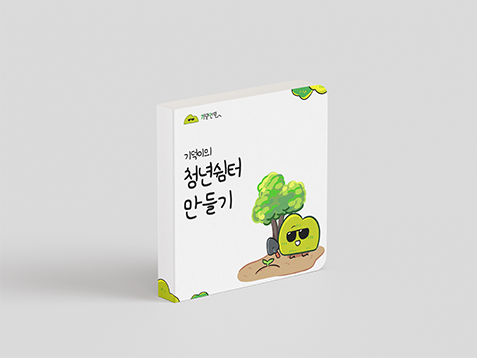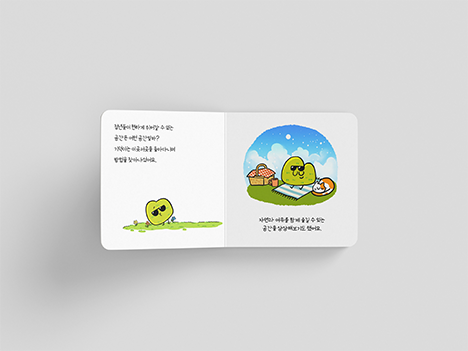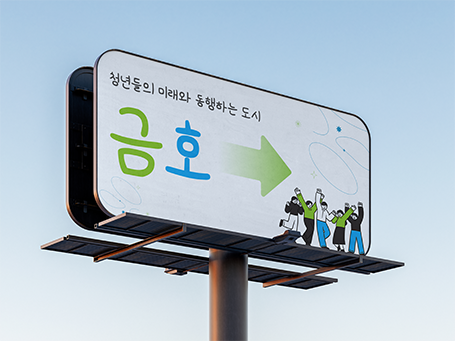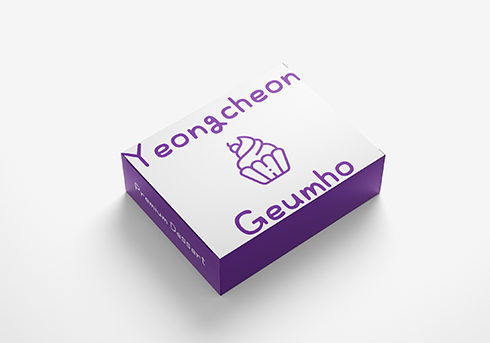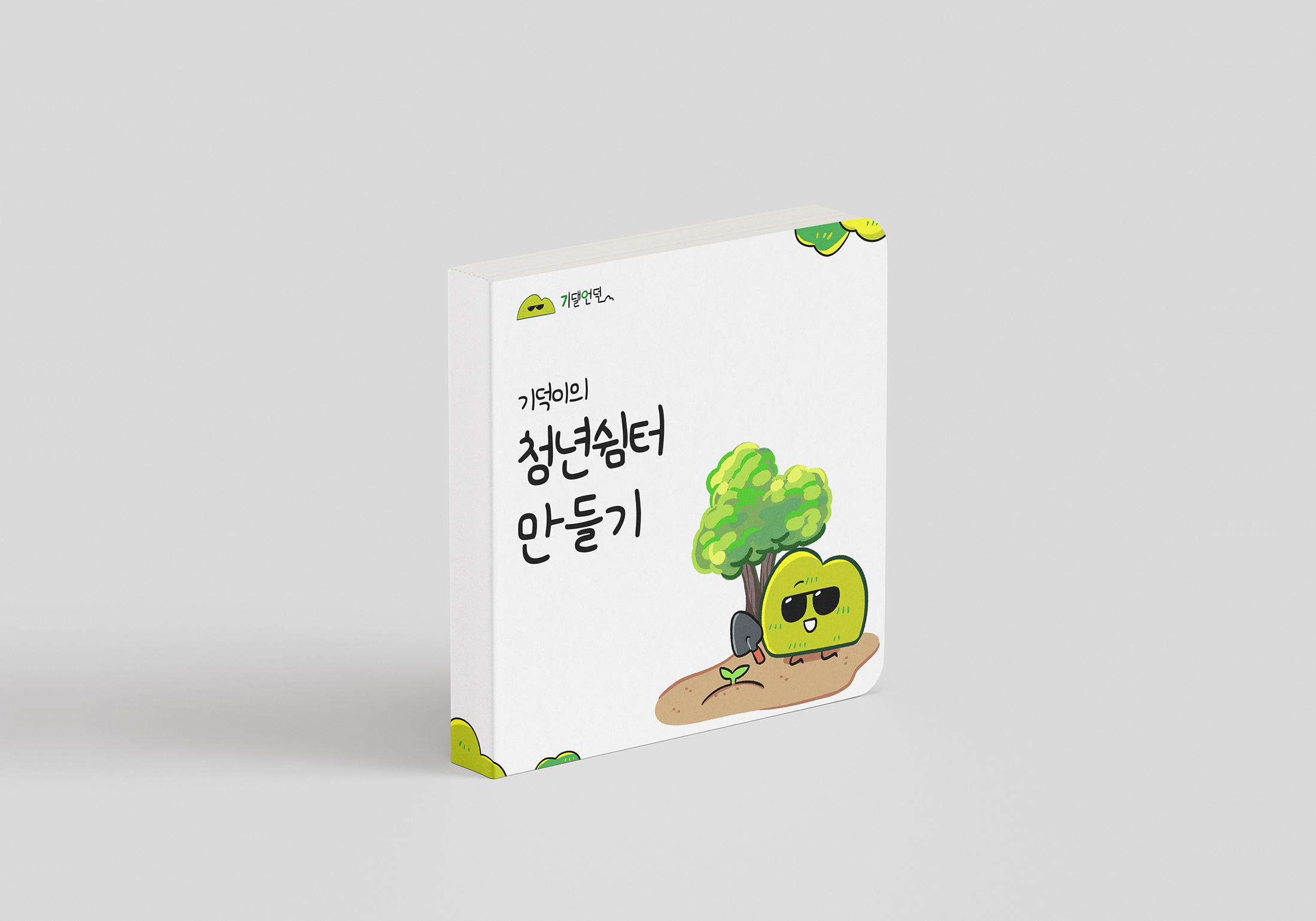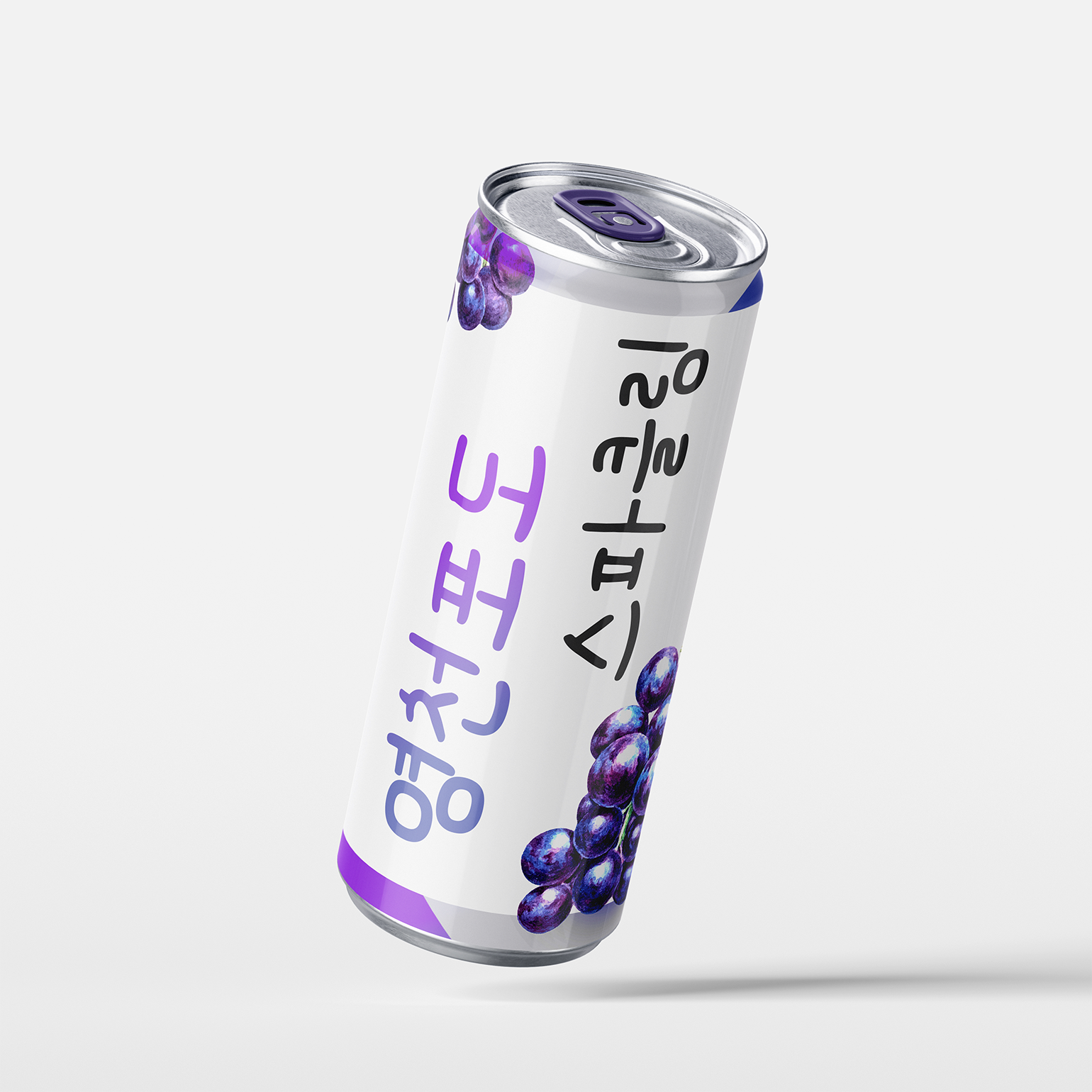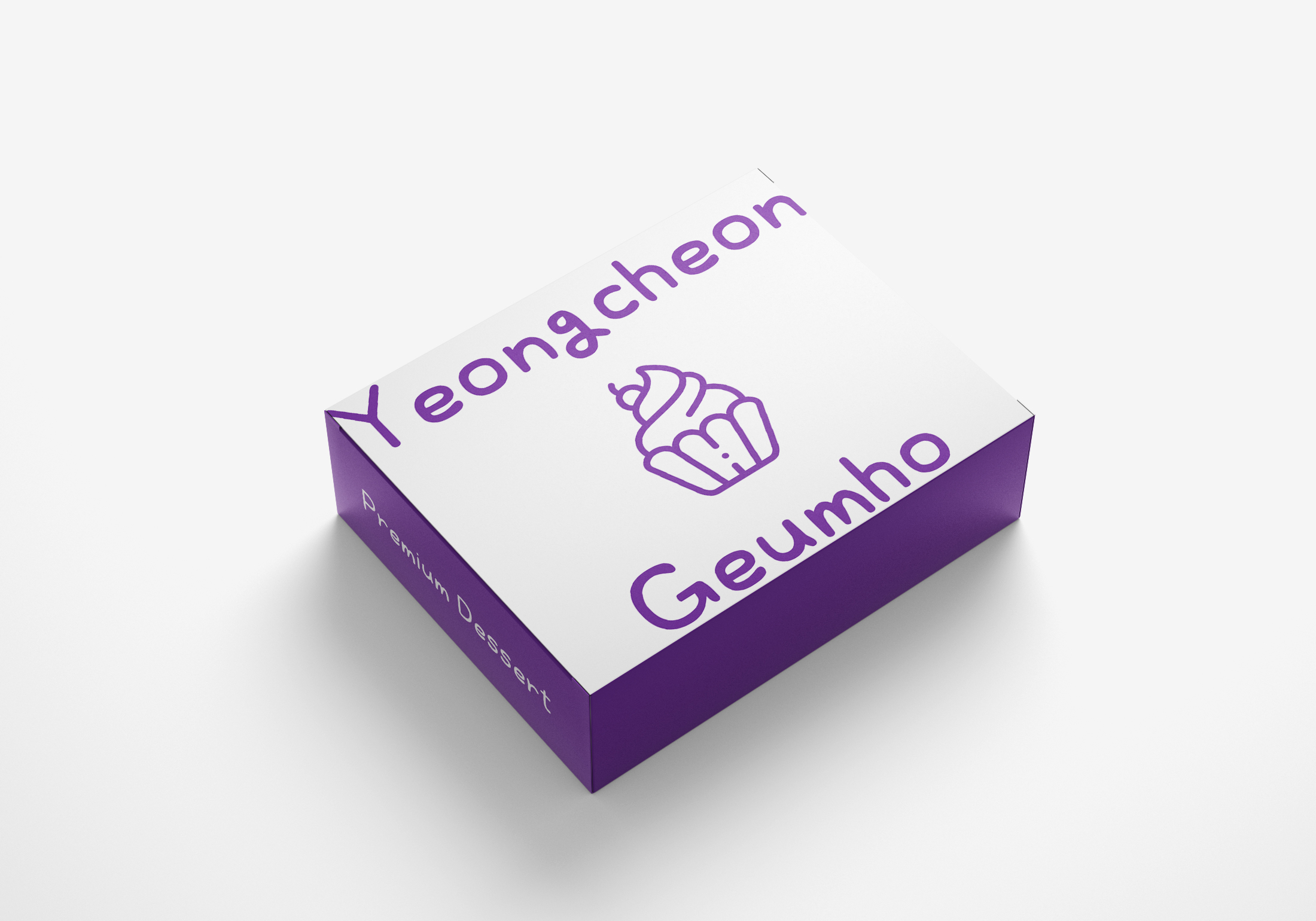
금호ON
청년과 금호를 잇-는 글씨
구성한 금호ON
청년과 금호가 함께 걸어가는
따뜻한 발걸음을
손글씨의 감성으로 담아낸 글씨체입니다.
획 하나하나에 담긴 부드러운 곡선은
서툴지만 진심 어린 청년들의 움직임,
그리고 이를 품어주는 금호의 포용을 상징합니다.
• 가나다라마바사아자차카타파하
• 0123456789
• abcdefghijklmnopqrstuvwxyz
청년과 금호를 잇 - 는 마음,
이제 글씨로도 이어집니다.
손으로 쓴 듯한 부드러운 곡선과
자유롭고 젊은 감성의 금호ON체를 직접 써 보세요.
금호ON를 활용한 작업물입니다.